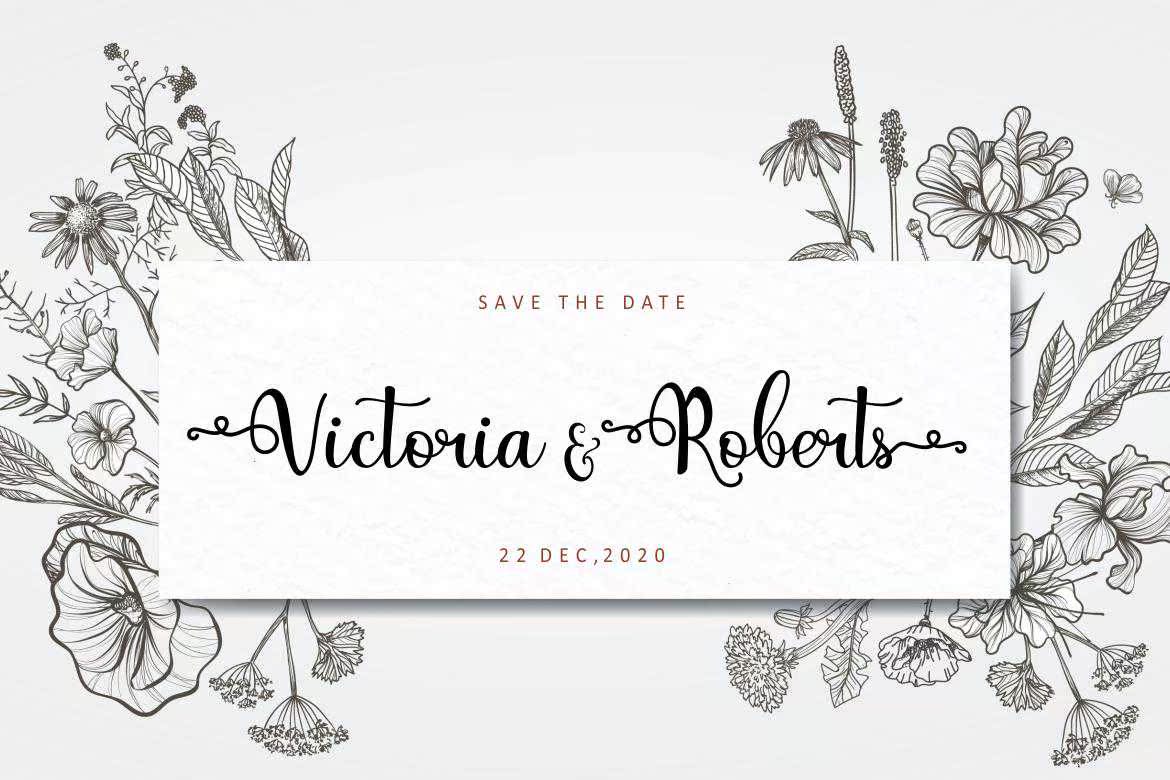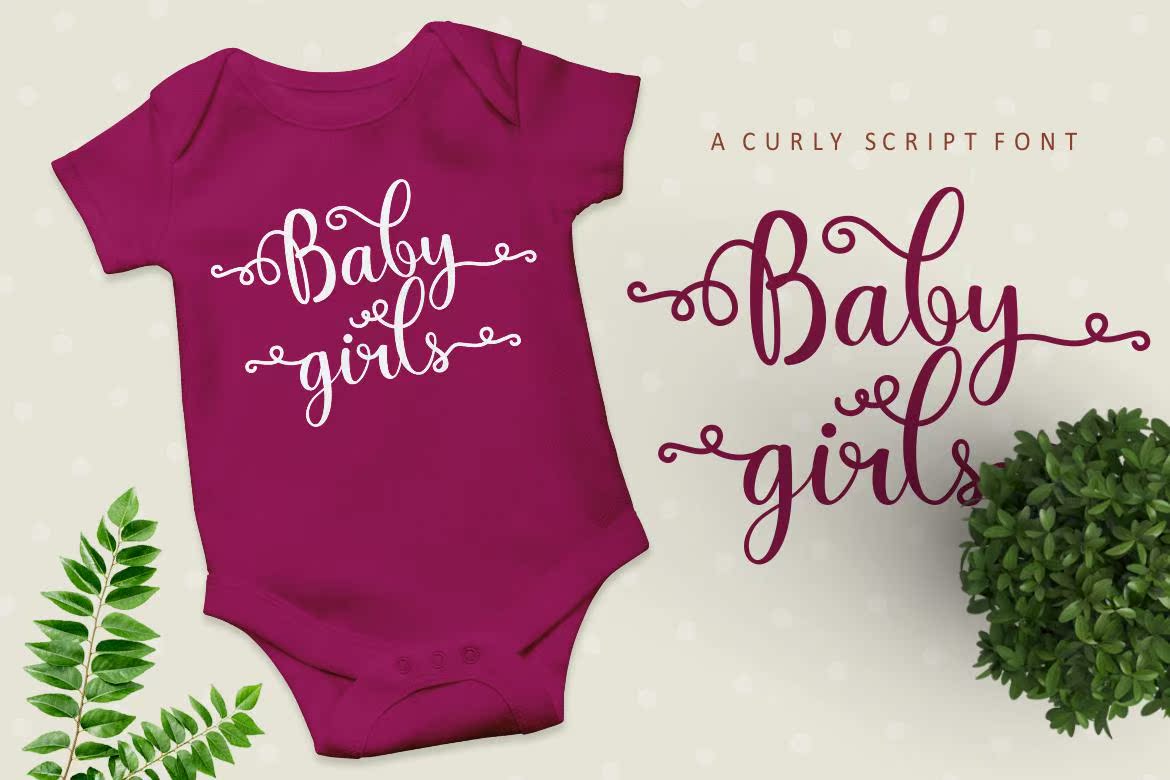
只需使用AcurlyTails旋转S amoder和FunScriptFonts。此集合对于FiftProducts Ashirts或ReingCards是完美的。您可以在孩子的礼物上旋转S amoder和FunScriptFonts并使用AcurlyTails。此集合对于FiftProducts Ashirts或ReingCards是完美的。您可以在孩子的礼物上旋转S amoder和FunScriptFonts并使用AcurlyTails。此集合对于FiftProducts Ashirts或ReingCards是完美的。您可以在孩子的礼物上旋转S是完美的塞吉特。